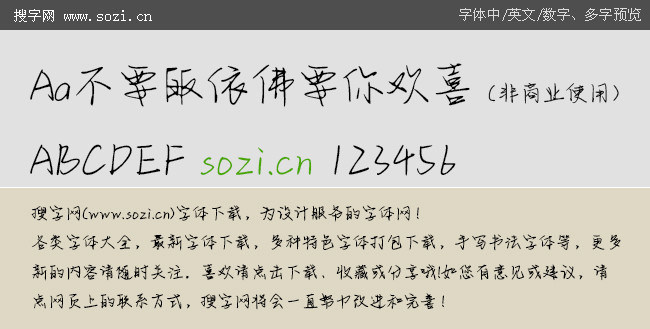
Aa不要皈依佛要你歡喜
搜字網(wǎng)給大家提供一款A(yù)a不要皈依佛要你歡喜(非商業(yè)使用)字體下載,該字體是一款手寫(xiě)風(fēng)格的中文字體,書(shū)寫(xiě)連貫,流暢自然,瀟灑大方。適合書(shū)裝設(shè)計(jì)、包裝設(shè)計(jì)、海報(bào)設(shè)計(jì)等應(yīng)用(此字體為個(gè)人非商用版,商用可以聯(lián)系QQ:1006760504)。